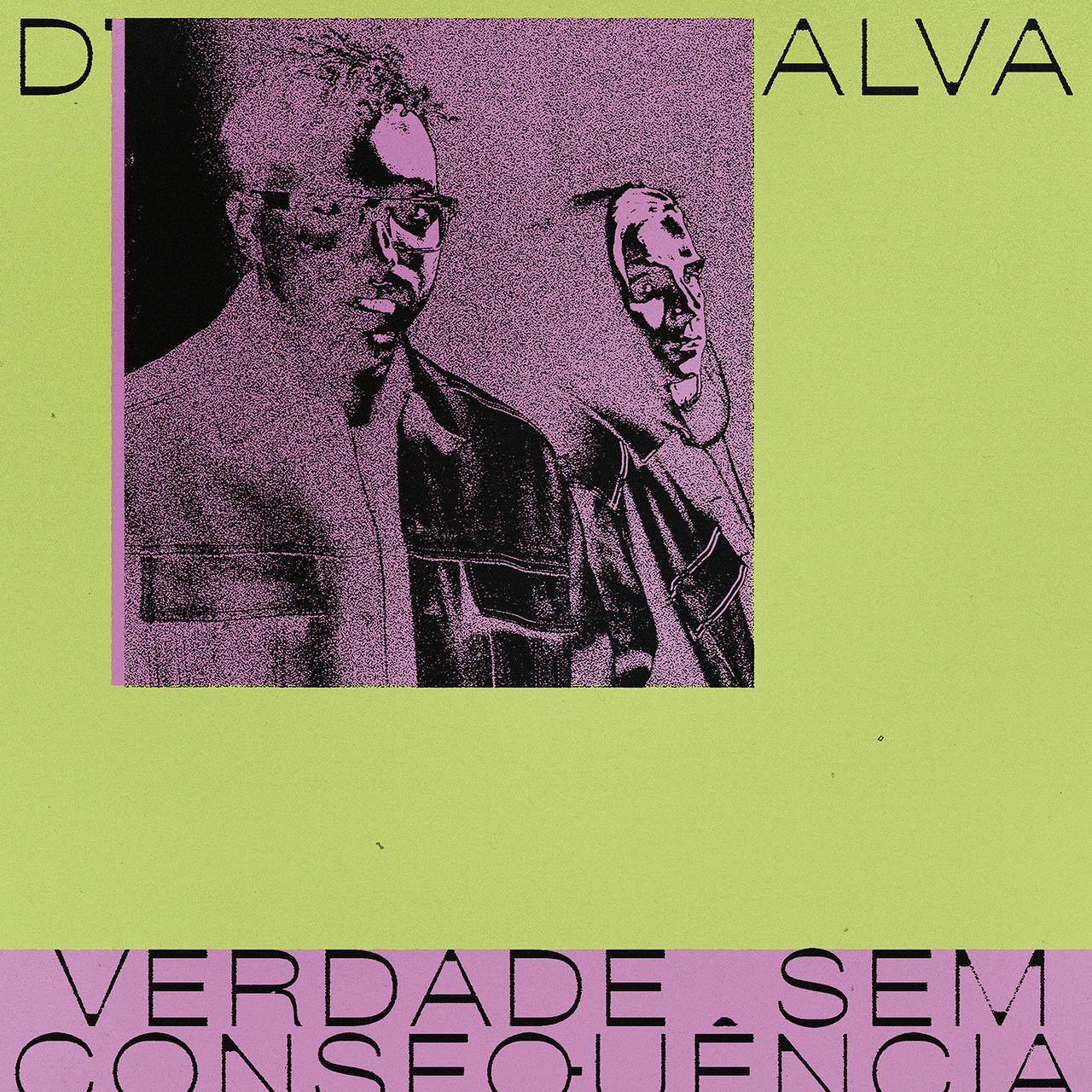
Suche Schrift des D'Alva Covers
Für ein persönliches Projekt suche ich die Schrift dieses Covers: https://braulioamado.tumblr.com/image/174240984507
Sie sieht ähnlich aus wie die Antipol: https://www.myfonts.com/products/extended-light-antipol-462684
Jedoch suche ich eine ohne diese Rundung. Bin froh um jeden Tipp 🙂
Gerade herausgefunden, dass es eine customized font ist, kennt jemand evt eine ähnliche, oder weiss was für keywords mich auf meiner Suche näher an sowas bringt?